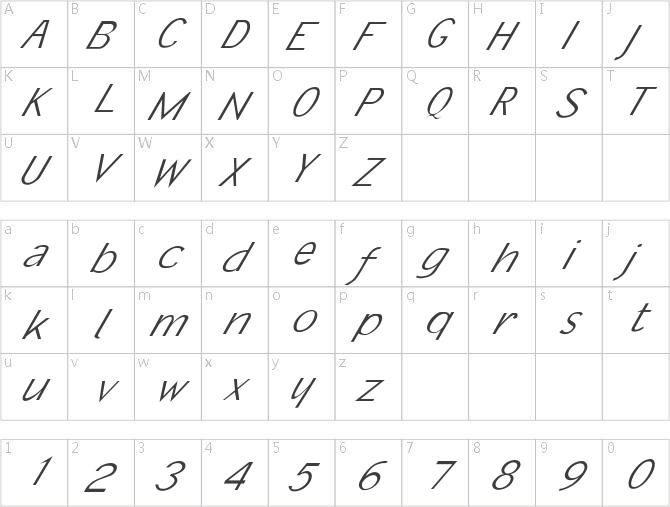
FZ BASIC 21 ITALIC
FZ BASIC 21 ITALIC介紹
FZ BASIC 21 ITALIC字體字庫是一款讓人賞心悅目、百看不厭的英文字體,適合各類廣告和產品包裝設計應用,字體大小0.04MB,格式為ttf字體,上傳用戶是rose,作者/版權方為未知
FZ BASIC 21 ITALIC效果圖